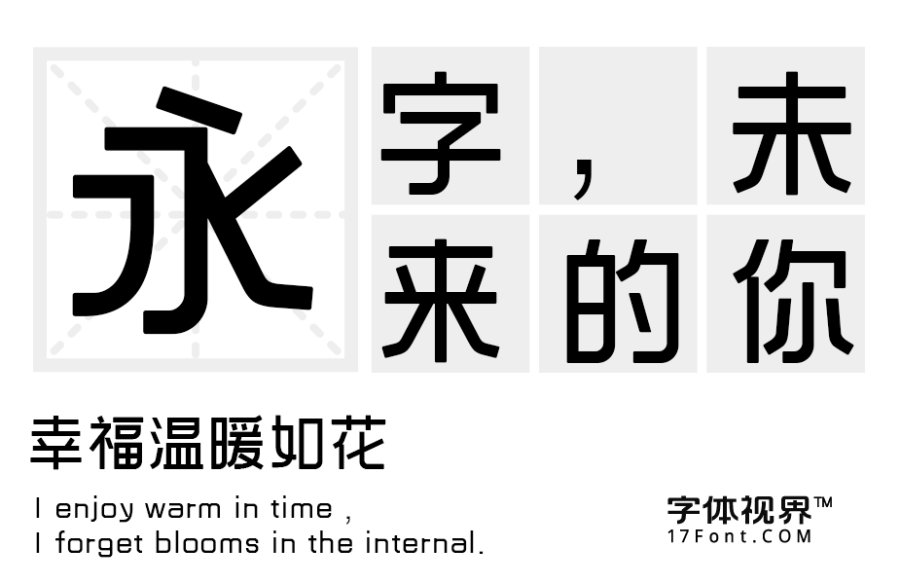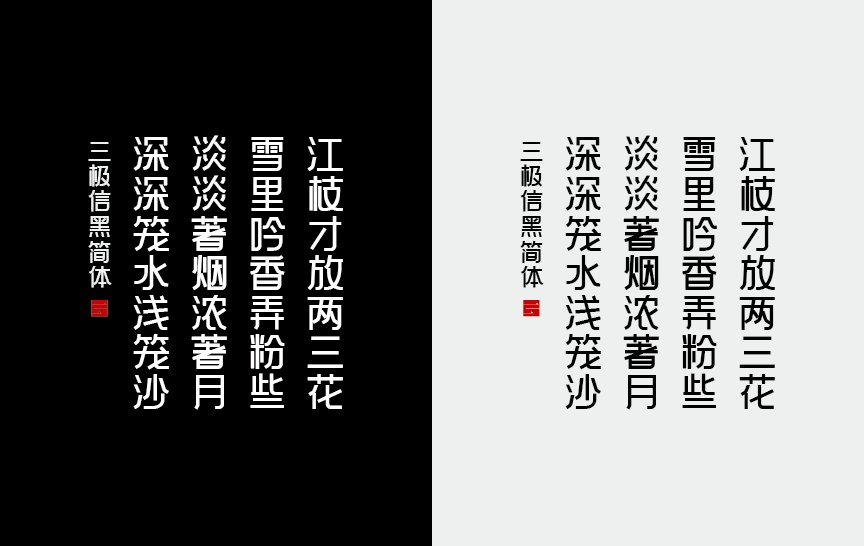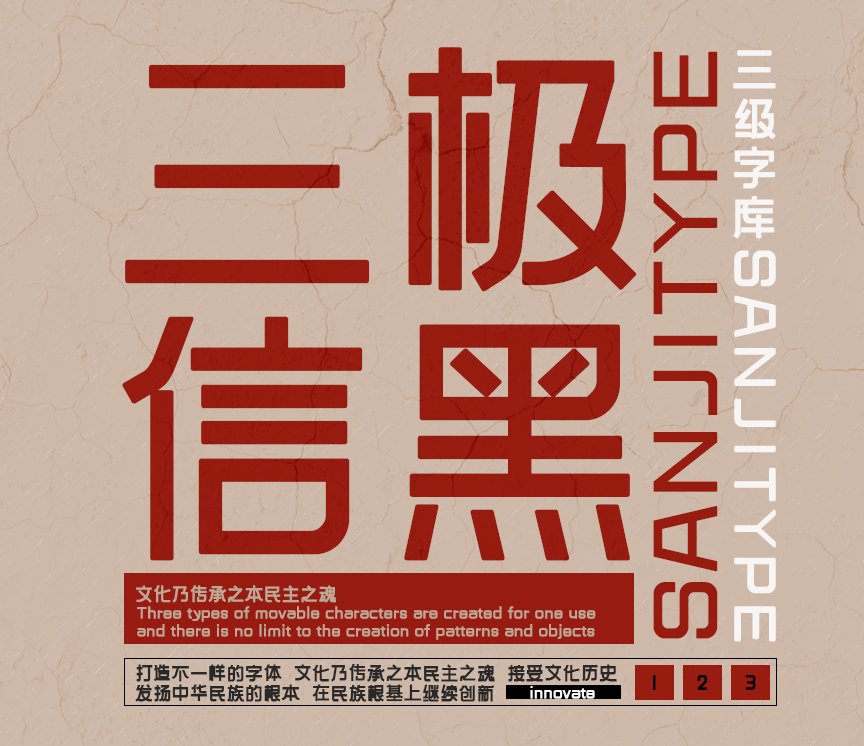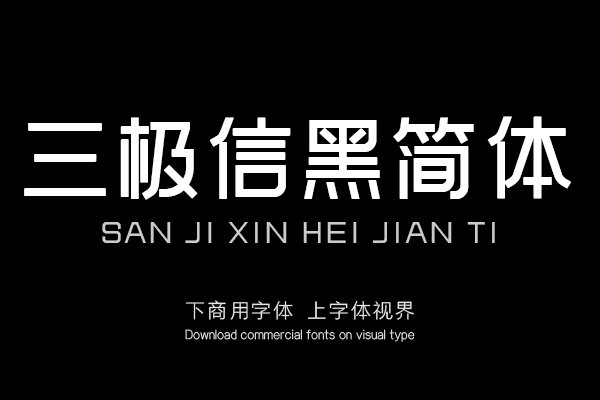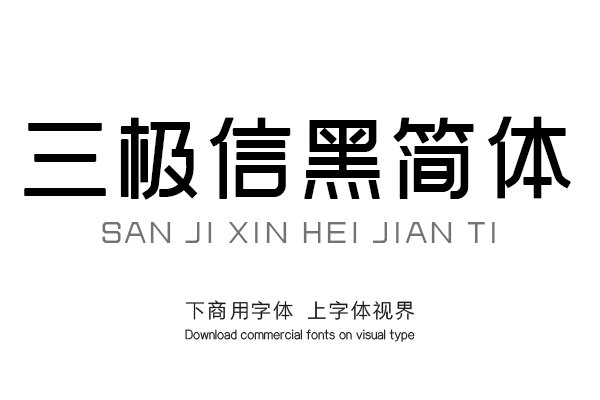
三极信黑简体是是一款几何感十足的创意字体。其笔画多以对称的手法来表现,撇、捺都有明显的几何转折,不同于书写状态的连续弧线。起笔收笔都为圆角,字体更加精致,使字体......购买须知:“下载服务费”与“字体VIP”所获得字体 仅用于个人非商用, 商用请联系付费授权。本字体为电脑用字,手机没有root权限不支持直接手机换字(手机如何root,请自行百度搜索教程)。购买前请先 了解清楚后再付款 ,字体为虚拟产品无法回收 一旦购买不支持退款。